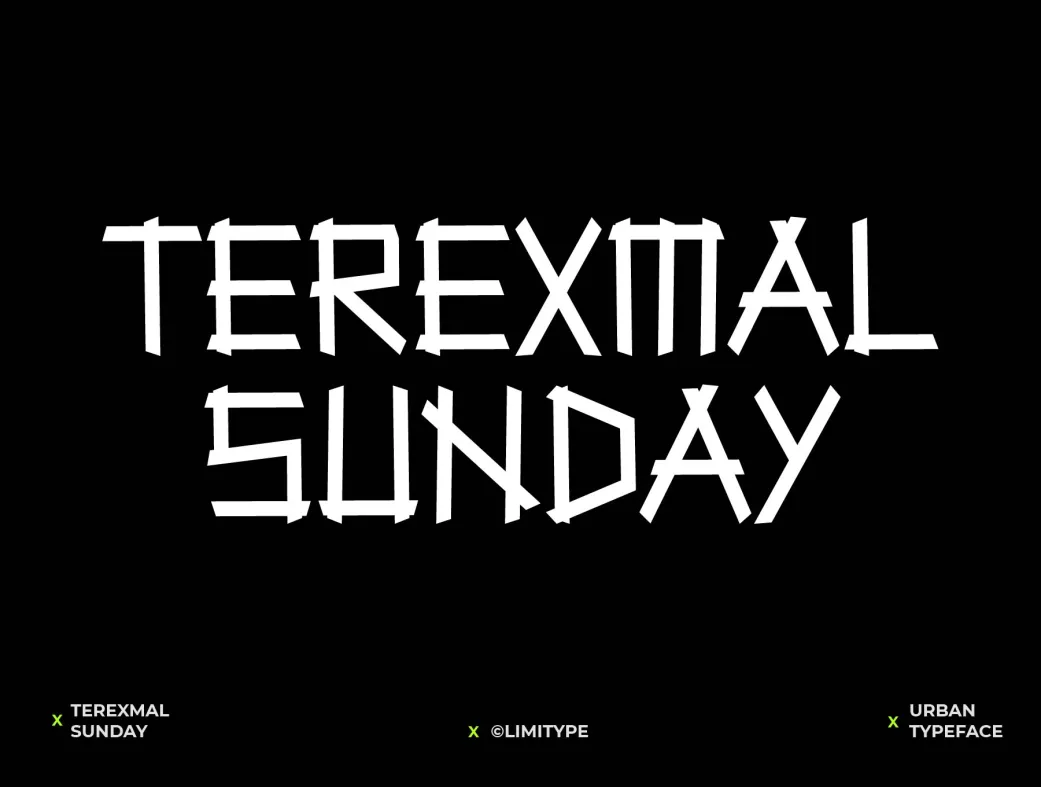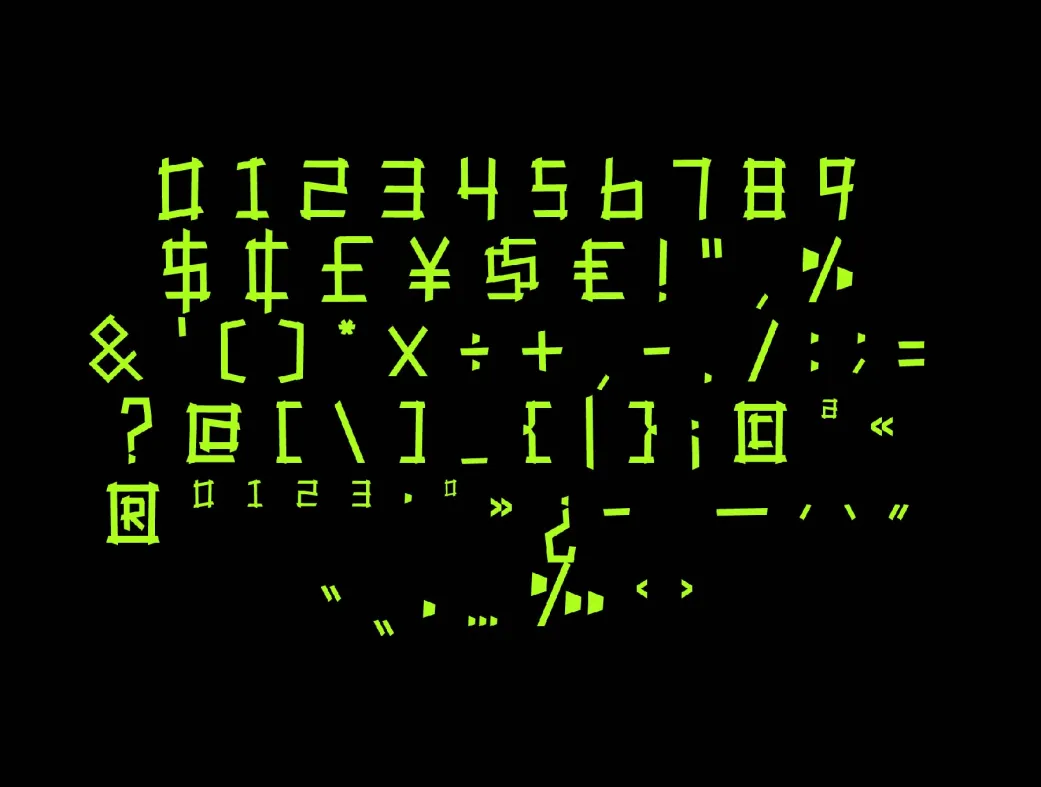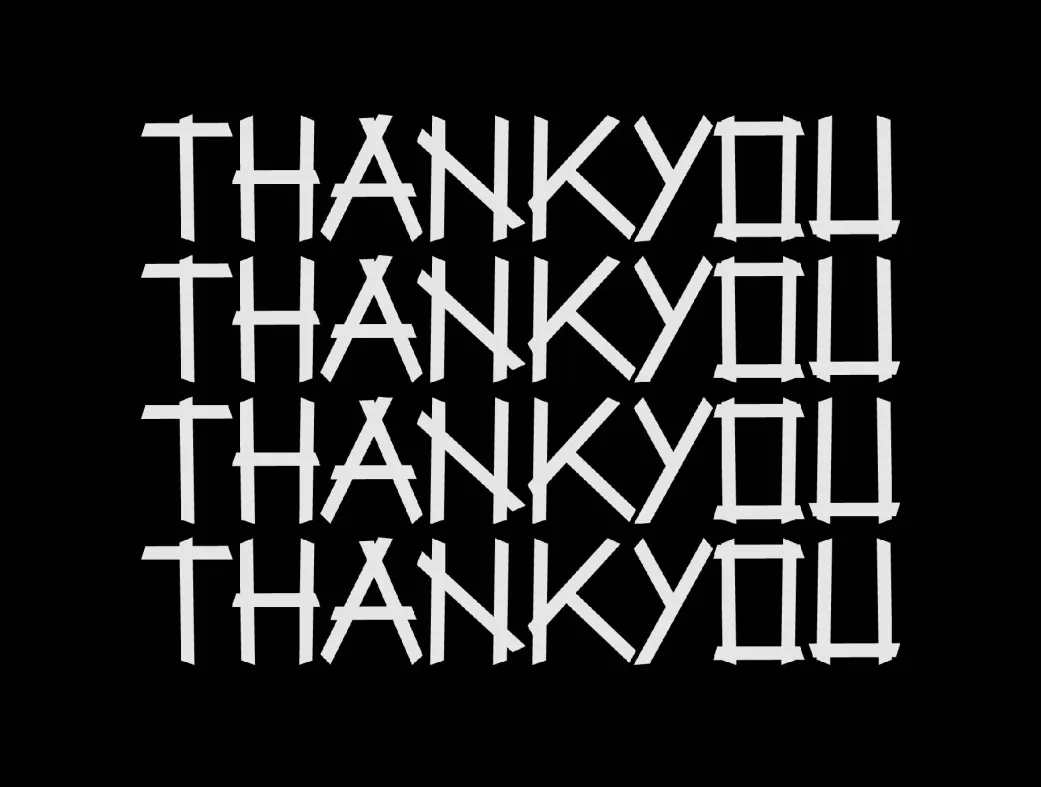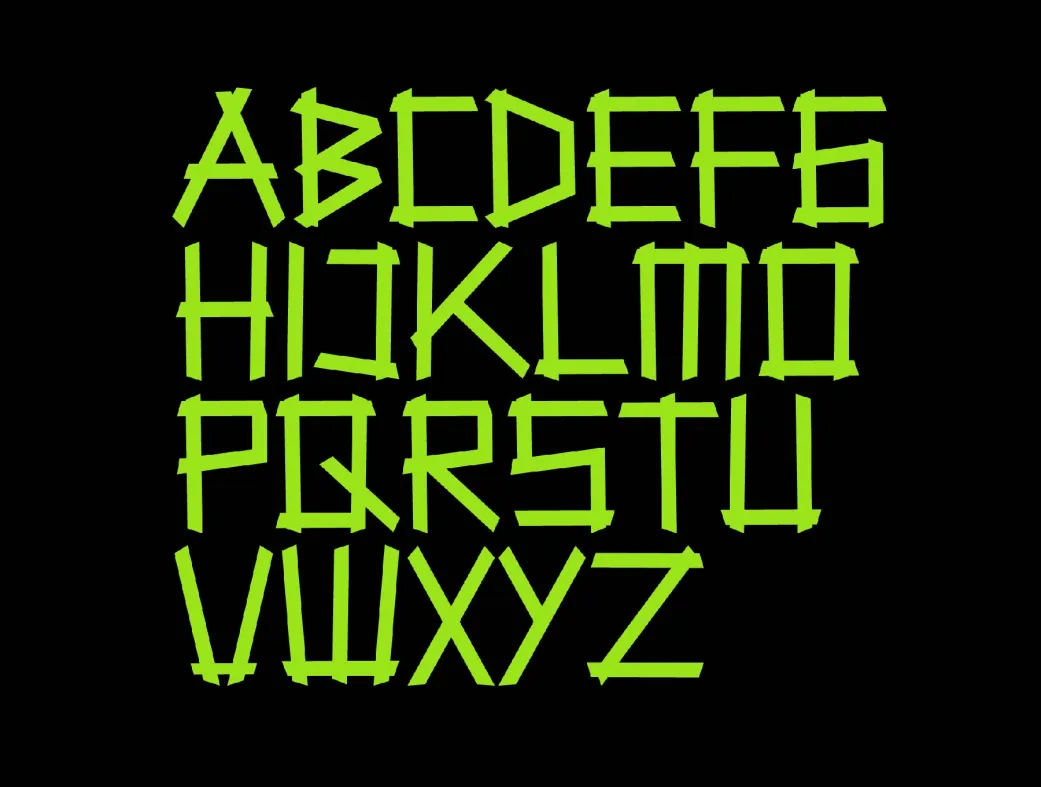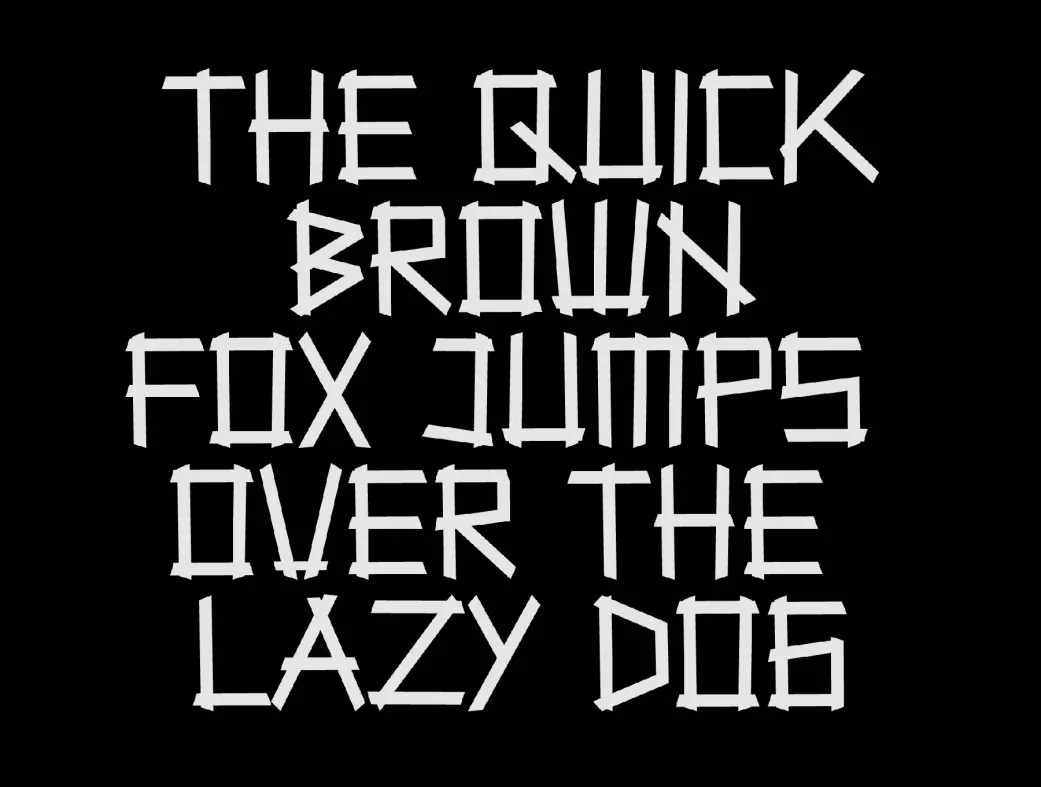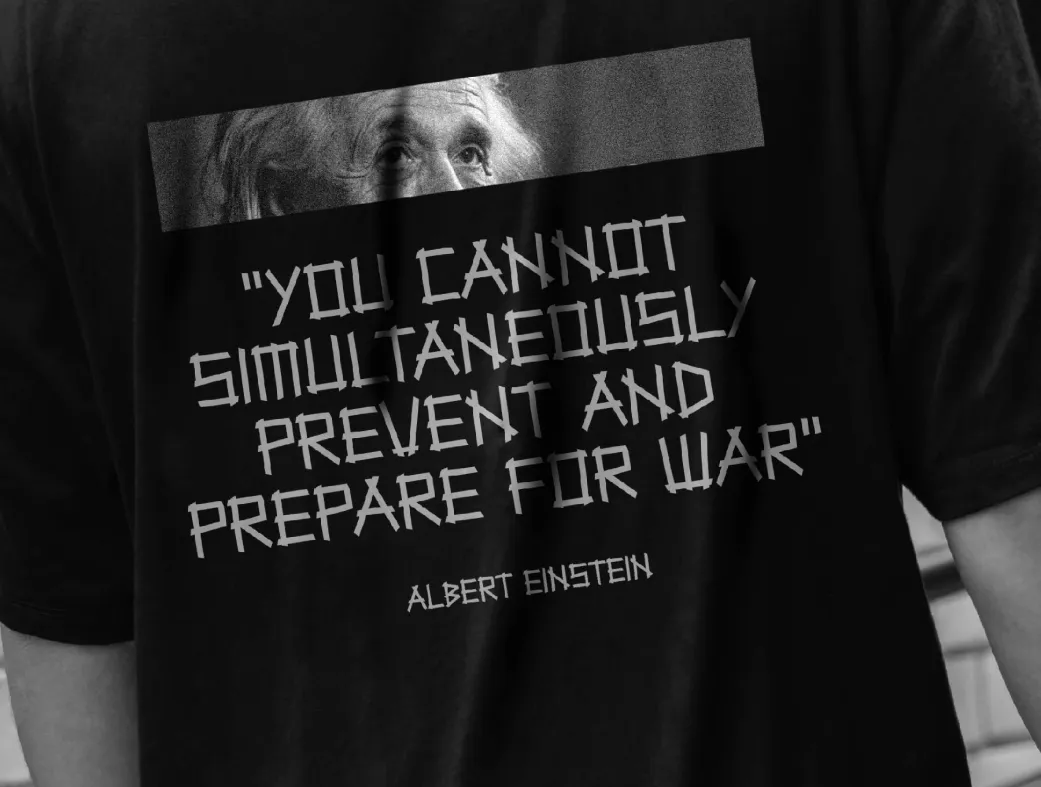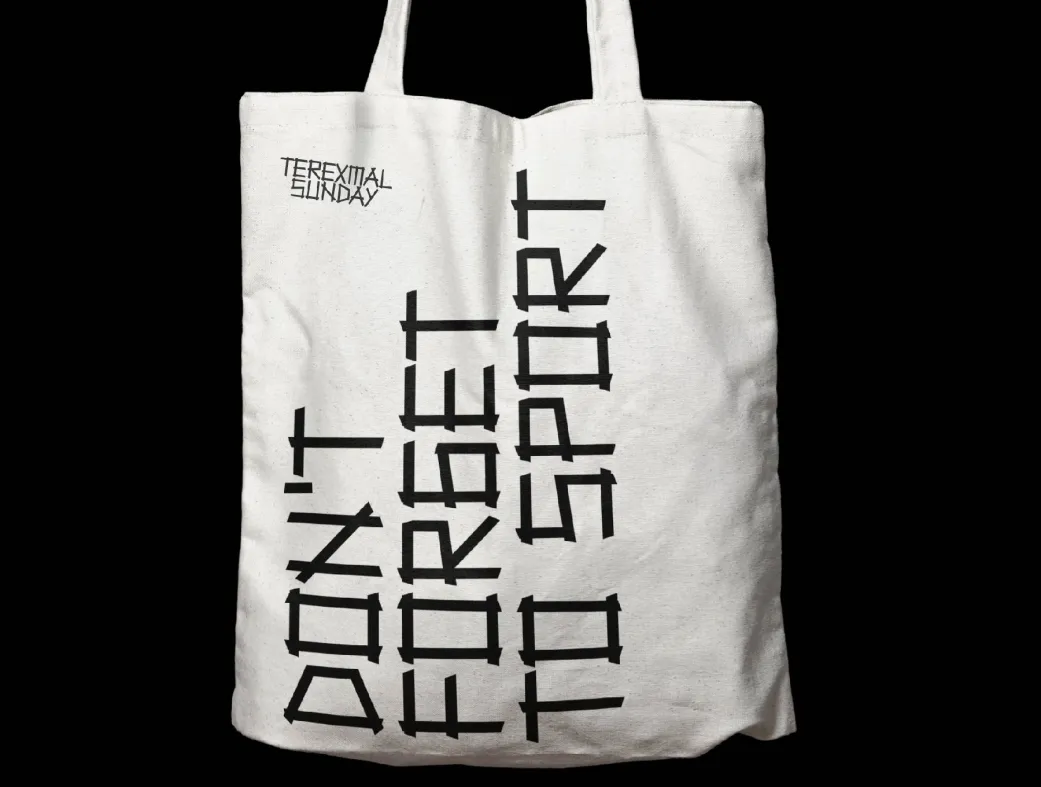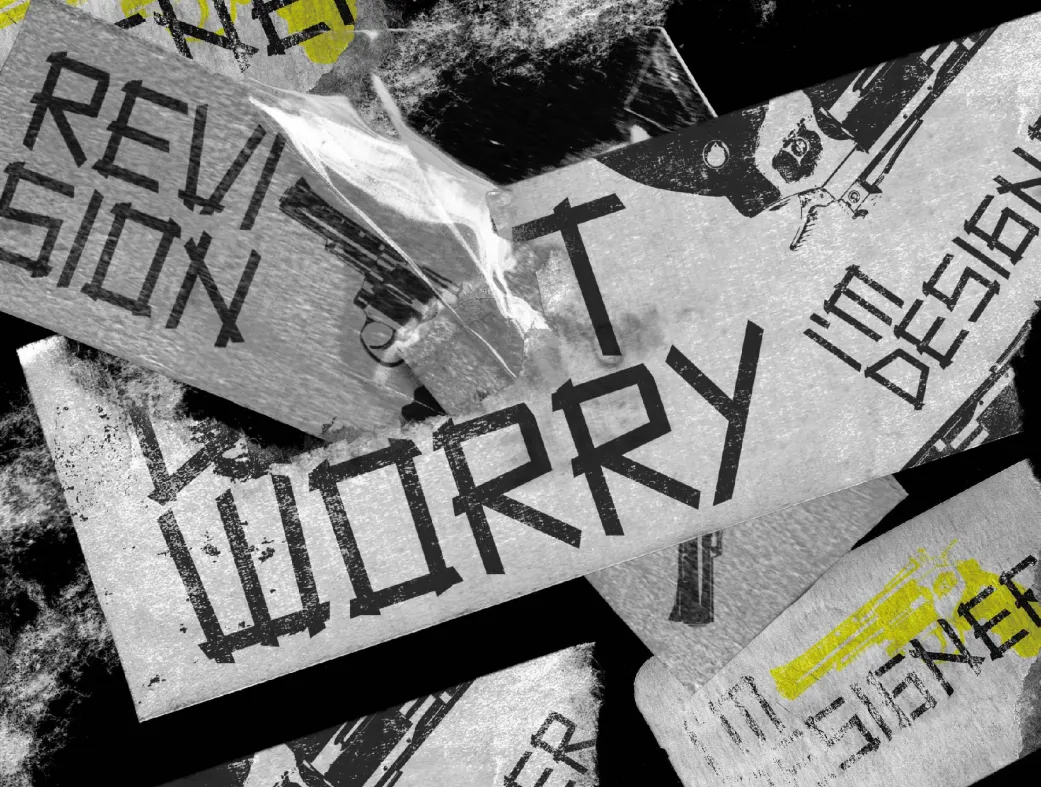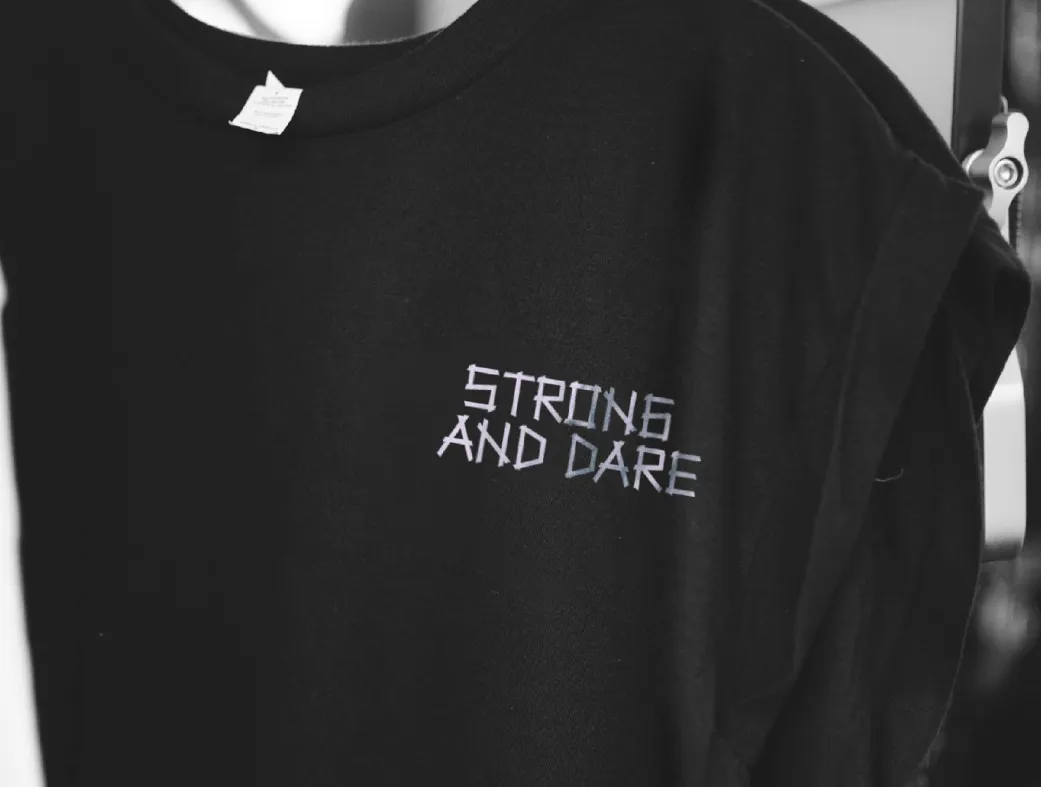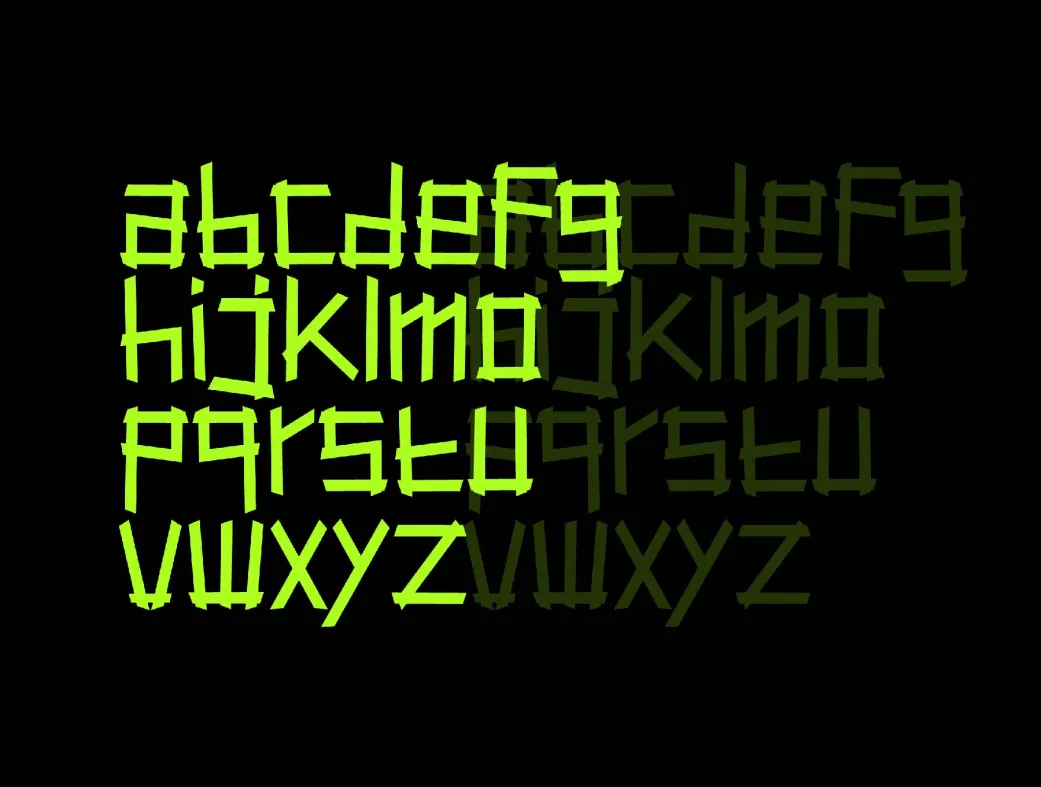
فونت مدرن و شهری رایگان ترکسمال سانده | Terexmal Sunday
فونت مدرن و شهری ترکسمال سانده، طراحی‌های شما را منحصر به فرد و جذاب می‌کند!
Terexmal Sunday - Modern Urban Font
فونت مدرن و شهری رایگان ترکسمال سانده | Terexmal Sunday | فونت تزئینی شهری
فونت ترکسمال سانده (Terexmal Sunday) یک فونت تزئینی با سبک مدرن و شهری است که ویژگی‌های منحصر به فرد و وحشی دارد، اما همچنان ظاهری مرتب و منظم ارائه می‌دهد. این فونت به طراحی‌های شما جلوه‌ای منحصر به فرد و جذاب می‌بخشد و به‌خصوص برای طراحی‌های مربوط به ورزش‌های جوانان مانند اسکیت، دوچرخه‌سواری، موتورسواری، کوهنوردی و موج‌سواری ایده‌آل است.
فونت ترکسمال سانده با حروف بزرگ و کوچک، اعداد، نمادها و برخی زبان‌های چندگانه ارائه می‌شود. این ویژگی‌ها به طراحان این امکان را می‌دهد که در پروژه‌های مختلف خود از این فونت استفاده کنند. طراحی مدرن و شهری این فونت، به ویژه برای جذب نگاه‌های جوانان و عاشقان فعالیت‌های ورزشی بسیار مناسب است. همچنین، این فونت به طرز خلاقانه‌ای می‌تواند به عنوان نقطه قوت در طراحی‌های گرافیکی، پوسترها، و تبلیغات مورد استفاده قرار گیرد.
با استفاده از فونت ترکسمال سانده، می‌توانید احساسات و انرژی جوانی را به طرح‌های خود اضافه کنید. این فونت به طرز شگفت‌انگیزی با دیگر عناصر طراحی ترکیب می‌شود و می‌تواند به شما کمک کند تا طراحی‌هایی با جذابیت بصری بالا ایجاد کنید.
• کاربران حرفه‌ای: این فونت برای طراحان گرافیک حرفه‌ای که به‌دنبال ایجاد طراحی‌های منحصر به فرد و مدرن هستند، بسیار مناسب است. می‌توانید از این فونت در پروژه‌های تبلیغاتی، پوسترهای ورزشی و وب‌سایت‌های مربوط به جوانان استفاده کنید.
3. آیا این فونت با زبان‌های مختلف سازگار است؟
بله، فونت ترکسمال سانده شامل حروف چندزبان و نمادهای مختلف است که به شما امکان می‌دهد در طراحی‌های خود از آن‌ها استفاده کنید.
4. این فونت برای چه نوع طراحی‌هایی مناسب است؟
این فونت به‌خصوص برای طراحی‌های مرتبط با ورزش‌های جوانان، پوسترها، تبلیغات و وب‌سایت‌ها مناسب است.